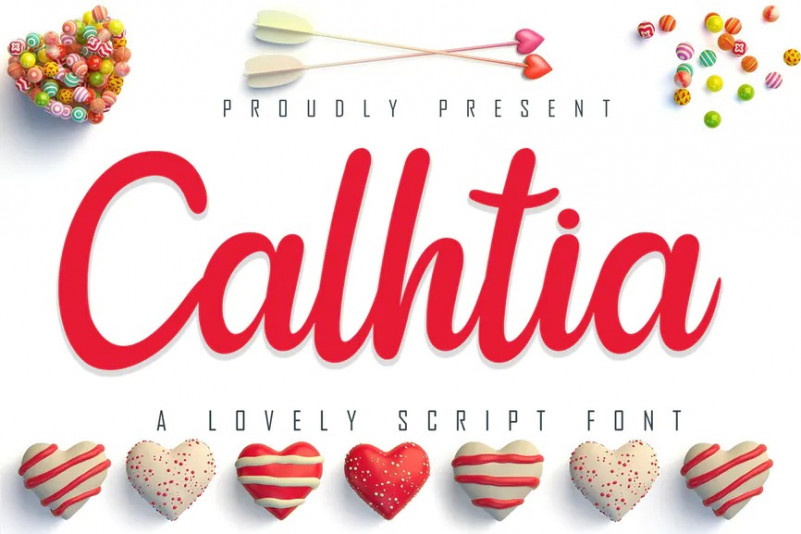
Calhtia Font
Calhtia est une belle police d’amour adaptée pour une utilisation professionnelle ou Commercial pour soutenir vos promotions telles que les dessins, bannières, Dépliants, vêtements et bien plus encore